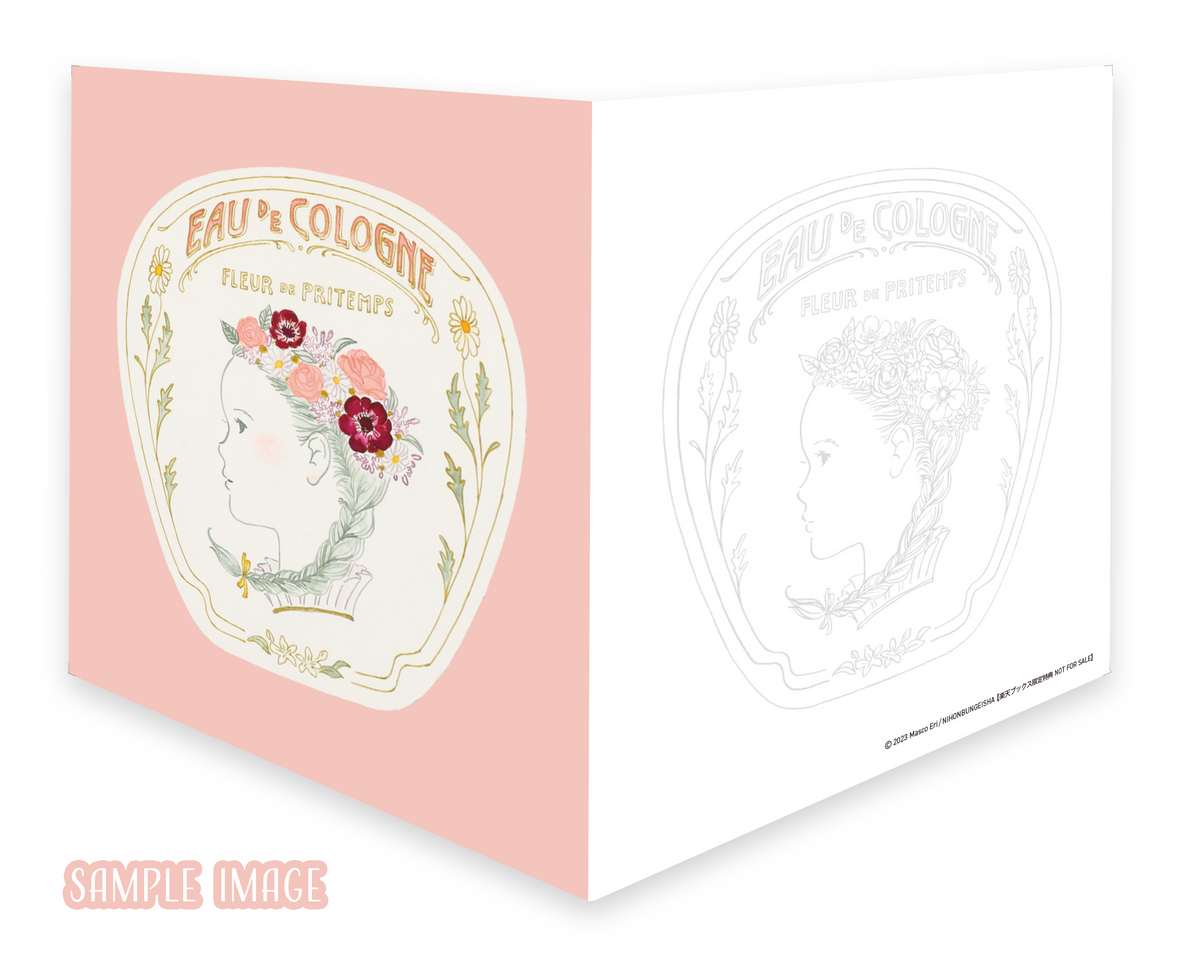
ガラスペンとインクでなぞる四季色ノスタルジー
株式会社日本文芸社は、ゆき氏監修による、人気イラストレーターますこえり氏のイラストが存分に味わえるなぞり描き本「ガラスペンとインクでなぞる四季色ノスタルジー」を2022年6月29日(木)より発売する。
「ガラスペンとインクでなぞる四季色ノスタルジー」は、人気イラストレーター・ますこえり氏のイラストが存分に味わえるなぞり描き本。
ガラスペンとお好みのインクで、ますこえりさんのどこか懐かしくてノスタルジックな描き下ろしイラストや文字をなぞるインクが好き、文具好き、紙好きさんのための、とことん「手描き」を楽しむための一冊となる。
ガラスペンに限らず、万年筆やラメペン、ミルキーペンなどでも楽しめる。
紙の種類は4種類。
手書きと相性が良いものを厳選し、文字は、ますこさんの手描き文字から多種多様なフォント(日本語・英語)を盛りこまれた。
イラストは春夏秋冬をテーマとし、すべて「ガラスペンとインクでなぞる四季色ノスタルジー」のための描き下ろしとなる。
ますこえり氏ならではの、愛らしくもクスッと笑える女の子や子どもたちとともに季節の移ろいを感じられるイラストばかり。
乙女心くすぐるかわいいパッケージやラメインクも活用できる夜空のデザイン、ついのぞき見したくなる日記など、イラストに合わせてインク×色数を選ぶのもまた一興。
自分でイラストを描くのが苦手な人も、丁寧になぞれば、ますこ氏のかわいいイラストが仕上がるはず。
「ガラスペンとインクでなぞる四季色ノスタルジー」では、インクの種類や使い分け方、ガラスペンの扱い方なども写真付きで解説します。ガラスペン初心者やインクの知識を深めたい人にもおすすめ。
1色でも、2色でも、多色でも、お好みのインクであなただけのイラストを仕上げて楽しめる、インク沼の住人のみなさんの心をくすぐる一冊。